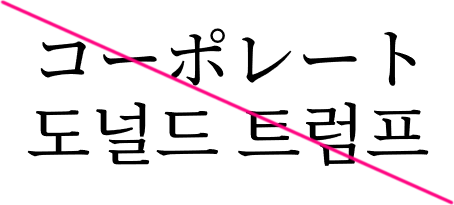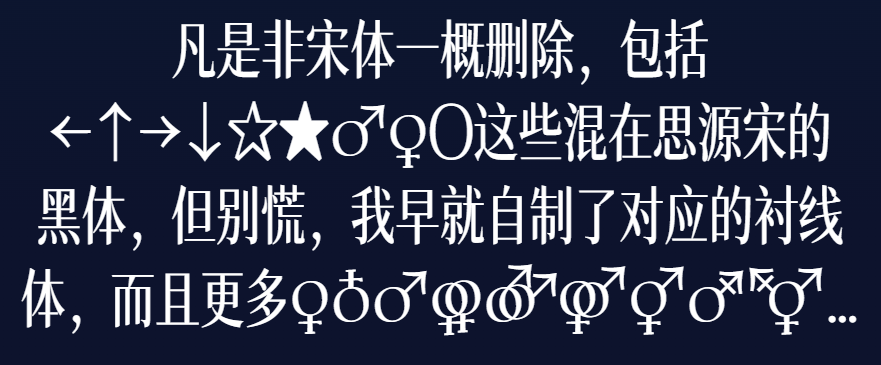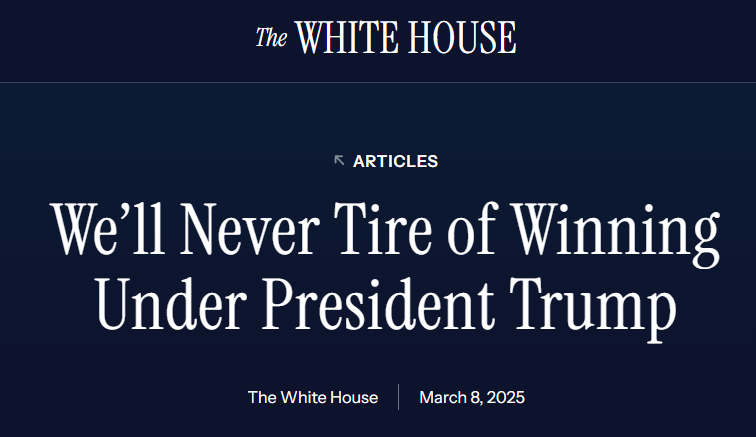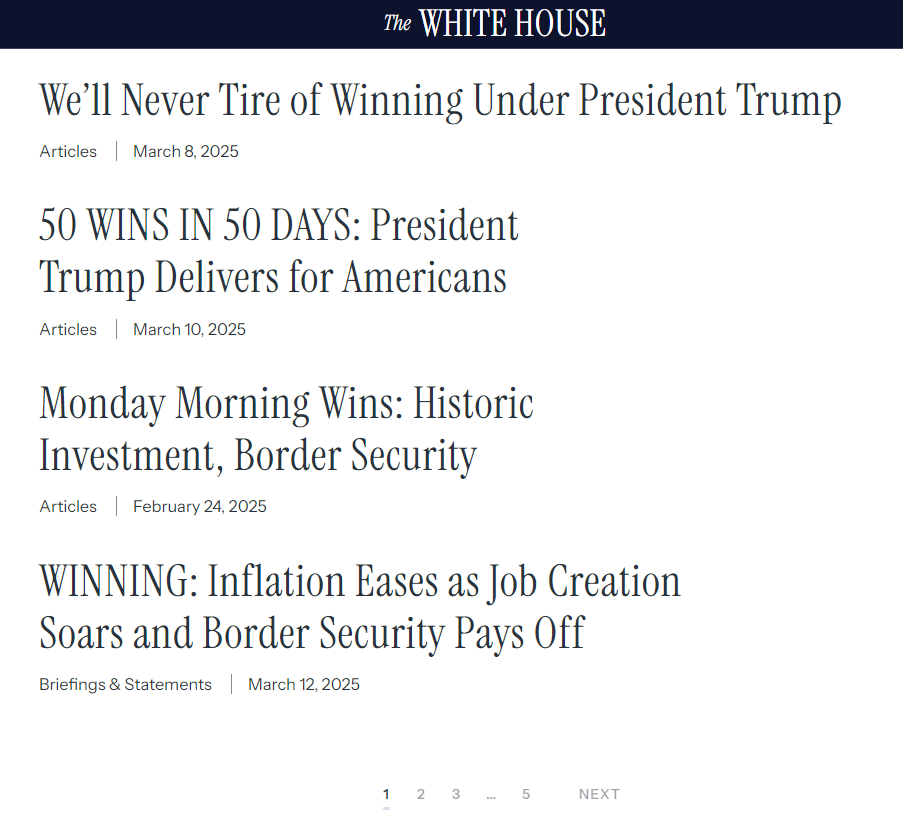
司源赢宋
清明回家突然想到,怎么没人给白宫官网这个标题字体搭配中文的。
右键检查了下,是个 OFL 授权的开源字体 Instrument Serif,1个字重及对应斜体(上图的“The”便是)
网上也有人做了模仿白宫官网的网页,但字体不到位,原因是,虽然 CSS 可以强行挤窄文字,但中英混排不佳。
与其纠结代码,何不预制一个现成的中英混排白宫字体?
一晚上做出来了,就叫“司源赢宋”,若软件不能显示中文名,其后备名称为“CorpSrcWinSong”。
显然汉字部分又是思源改。由于Source Han Serif © Adobe, with Reserved Font Name 'Source'.
所以思源改不让用“思源Source”为名,因此字体名用“Src”,“源”。
既然名为“宋”,当然只能是宋体,凡是非宋体字形一概删除⸺思源宋的假名、注音、谚文就都删了。
虽说有宋体谚文,但不是 OFL 的(如有请告知!)
不过,存在 OFL 的宋体假名,可能有些人已经见过:
以上动画截屏中的宋体为コーポレート明朝 ver1旧版(Corporate Mincho,作者自己缩写为“corpmin”)所以字体名用“Corp”,“司”。而我曾经给 ver2 补过字(源意明朝),稍微省了点事⸺ver3 何时来的1
一概删除的也包括←↑→↓☆★♂♀〇这些混在思源宋里的黑体,但别慌,我早就自制了对应的衬线体,而且更多:♀♁♂⚢⚣⚤⚥⚦⚧…毕竟性别这个事嘛……
为方便网络传播,对该字体作了极限施压(slim)削到只剩6760常用汉字,因此实际文件名是CorpSrcWinSong-slim,其中网页字体(.woff2)版低至1MB,且完全保留原 Instrument Serif 既有的英文特性,如qj替换字形。
这次没做什么彩蛋,只附赠了个删除涂改线符号“␥”U+2425 SYMBOL FOR DELETE FORM TWO
如果还需要什么字请在评论中列举,像“”、元素周期表等在0.002-slim版确实是缺的⸺毕竟我给思源宋本体补字也不止一两次了⸺如果这字体用得着的话。(4月6日0.1版更新补全了这些字)
- 检查了Corporate Mincho ver3,发现字体文件结构问题颇多,ver2漏做的字(ゔゕゖヷヸヹヺ)还是漏,反而我补的全,可能作者用的软件有问题。另外圆体(Rounded)ver3字形还不如旧版圆。 ↩︎
未来计划
- 修改“费”字,补充“祎”字,等。
- 为了更加精简,
.woff2(网页字体)与.ttf字体分叉,某些几乎用不到的字仅在.ttf,不包含于.woff2中。
- 字体设计师: MY1L
- 字体描述: Instrument Serif; Corporate Mincho ver2; Source Han Serif; MY1L Serif
修改:哺埔捕脯式弑试国看踯()゛゜ゝゞ・ヽヾ,全部汉字确认为等宽
将dlig补充到liga
补充:█々亖啫啰巽瞭隆鿏鿔鿭鿬鿫